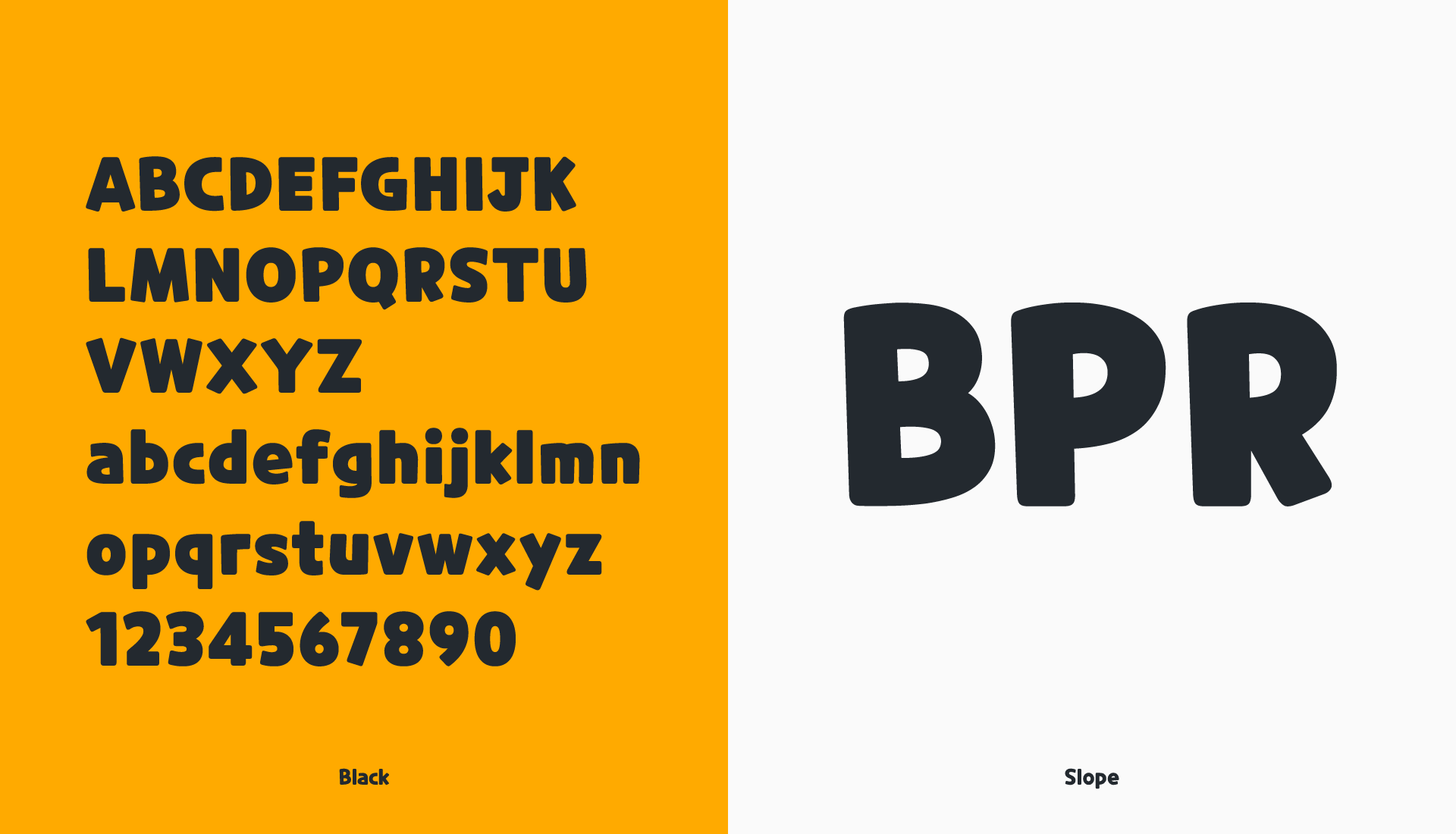
Font Việt hóa SRN CookieRun , Có thể gõ Tiếng Hàn
Mô Tả Font Việt Hóa SRN CookieRun – Gõ Tiếng Hàn Dễ Dàng
Giới Thiệu:
Font Việt hóa SRN CookieRun là bộ font chữ đáng yêu, lấy cảm hứng từ tựa game nổi tiếng CookieRun. Được thiết kế tối ưu cho người dùng Việt, font hỗ trợ đầy đủ dấu tiếng Việt và khả năng gõ tiếng Hàn, phù hợp cho thiết kế, game, quảng cáo hoặc nội dung mạng xã hội.
Đặc Điểm Nổi Bật:
✔ Hỗ trợ đa ngôn ngữ: Gõ tiếng Việt chuẩn Unicode, kết hợp với bảng chữ cái tiếng Hàn (Hangul).
✔ Phong cách game đáng yêu: Nét chữ tròn trịa, sinh động, mang đậm phong cách CookieRun.
Kết Luận:
SRN CookieRun là font chữ hoàn hảo cho fan game CookieRun và người yêu thích phong cách chữ dịu dàng, đa ngôn ngữ. Tải ngay để sáng tạo những thiết kế độc đáo!